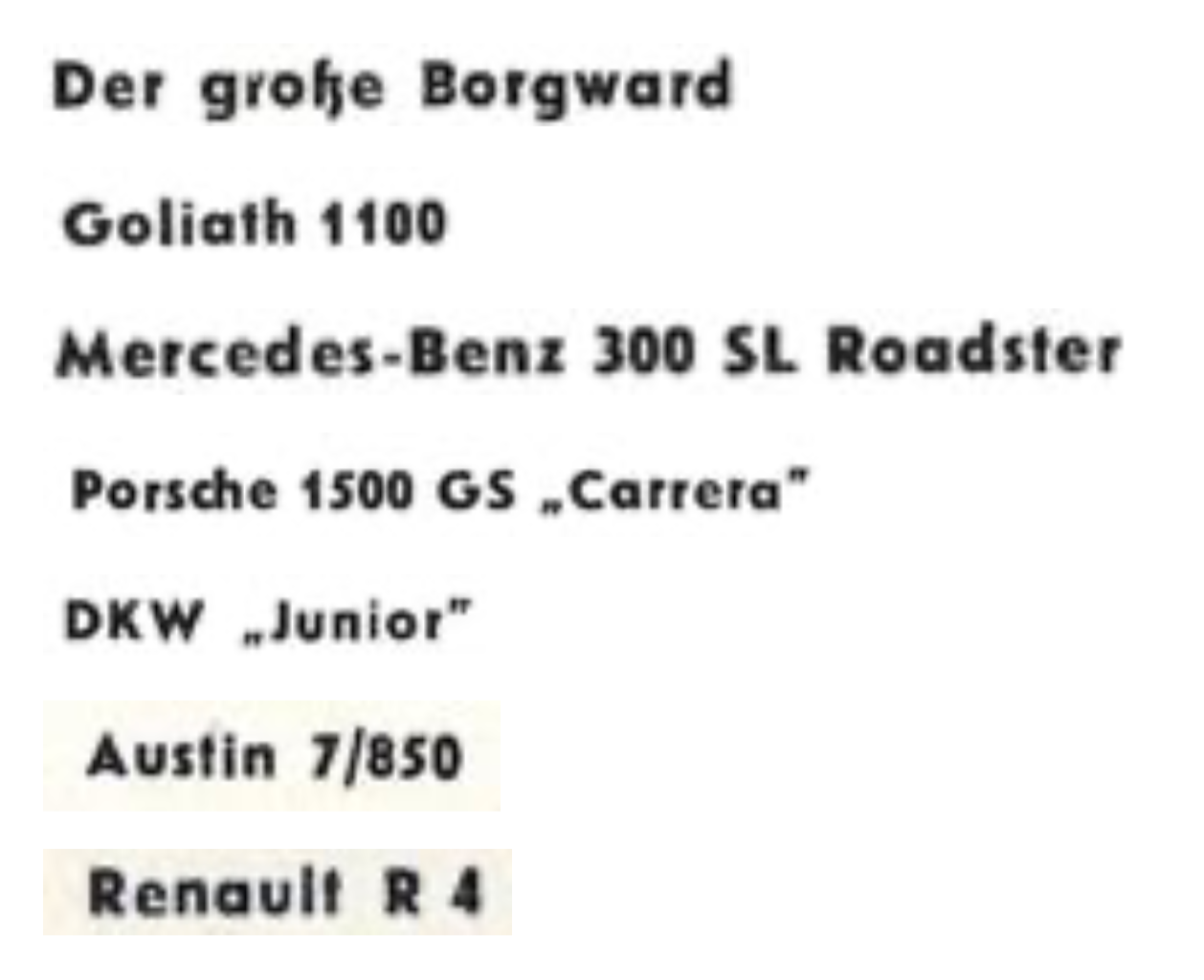
Suche Schrift aus ASS Quartetten von 1958 - 1963
Für Recherchezwecke suche ich genau diese Schrift. Sie taucht in den ASS Quartetten von 1958 - 1963 auf.
Ich habe versucht viele unterschiedliche Zeichen darzustellen. Wenn noch andere benötigt werden, kann ich suchen, ob sie auftauchen.
Fonderkennungsprogramm sind damit völlig überfordert, aber bei Euch bin ich mir sicher, dass Ihr die Schrift erkennt.
Die ähnlichste Schrift die ich gefunden habe ist "Erbar Bold", denn da passt das markante "ß" sehr gut. Leider ist da das "a" nicht korrekt.